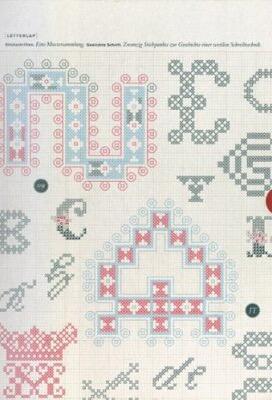
Letterlap ist ein zweiteiliges Werk, bestehend aus einem Leseheft und einer Schriftmustersammlung in Faltblattform.
In dem 64-seitigen Leseheft verschafft der Autor Jan Wenzel zunächst einen kurzen Einblick in die Kulturgeschichte des Stickens, um anschließend auf die Gestaltung von Buchstaben und Ziffern, mit Hilfe der Stick-Technik, ausführlicher einzugehen.
Auf sieben A1-Faltblättern sind insgesamt sechzig Stick-Schriftmuster abgebildet, welche von Janine Thaler recherchiert und für Letterlap digitalisiert wurden. Im Anhang des Lesehefts werden sämtliche Schriftmuster noch einmal verkleinert abgebildet und durch Zusatzinformationen ergänzt.
Letterlap besticht durch eine feinsinnige Typografie in ausgezeichneter Druckqualität und -veredelung.
Untertitel: Gestickte Schrift. Zwanzig Stichpunkte. Stickschriften. Eine Mustersammlung.